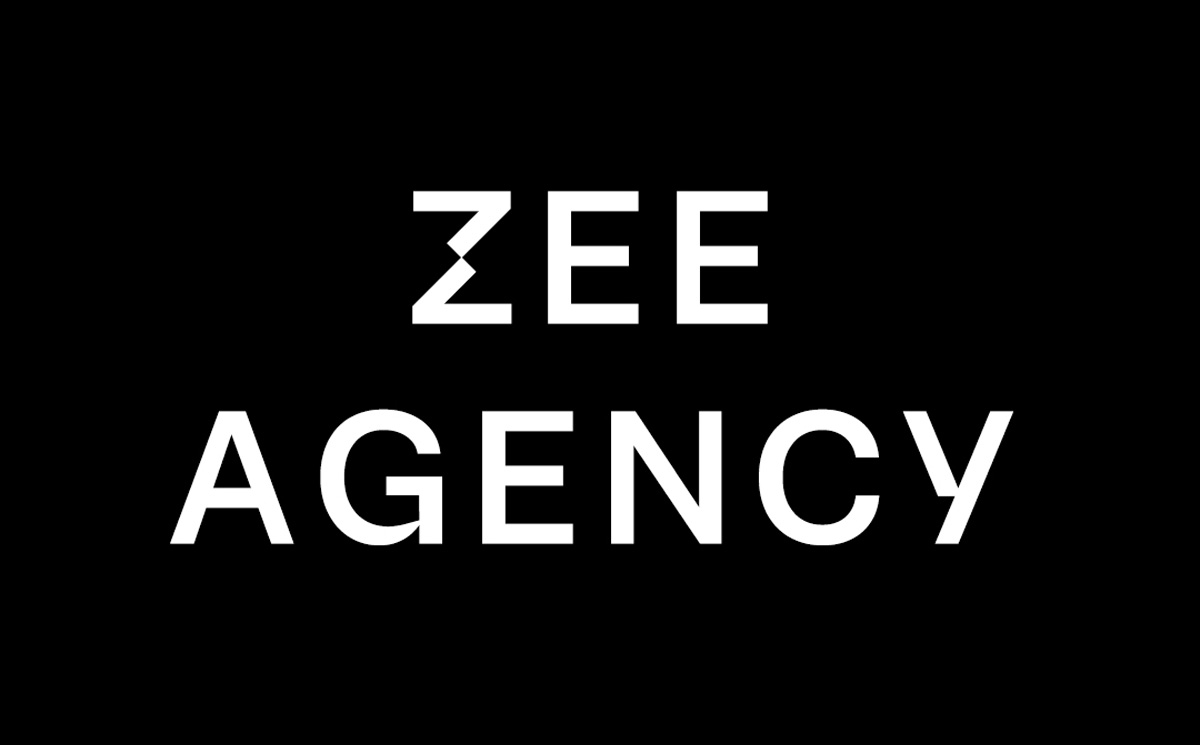
Font chữ chân phương là gì và phong cách tối giản trong đồ họa?
Font chữ chân phương là nhóm các phông chữ có cấu trúc ký tự rõ ràng, ngay ngắn và không quá cầu kỳ về mặt họa tiết. Từ “chân phương” trong ngôn ngữ Việt gợi nhắc đến sự mộc mạc, thành thật và chuẩn mực. Trong thiết kế, dòng phông này thường bao gồm các bộ Sans-serif hoặc Serif hiện đại với độ cao chữ đồng đều, giúp người đọc dễ dàng tiếp nhận thông tin mà không bị xao nhãng bởi các đường nét uốn lượn phức tạp.
Sức hút của phông chữ chân phương nằm ở tính minh bạch và sự vững chãi. Khi đơn vị ứng dụng kiểu chữ này vào hệ thống nhận diện, nó truyền tải thông điệp về một phong thái làm việc bài bản, đáng tin cậy.
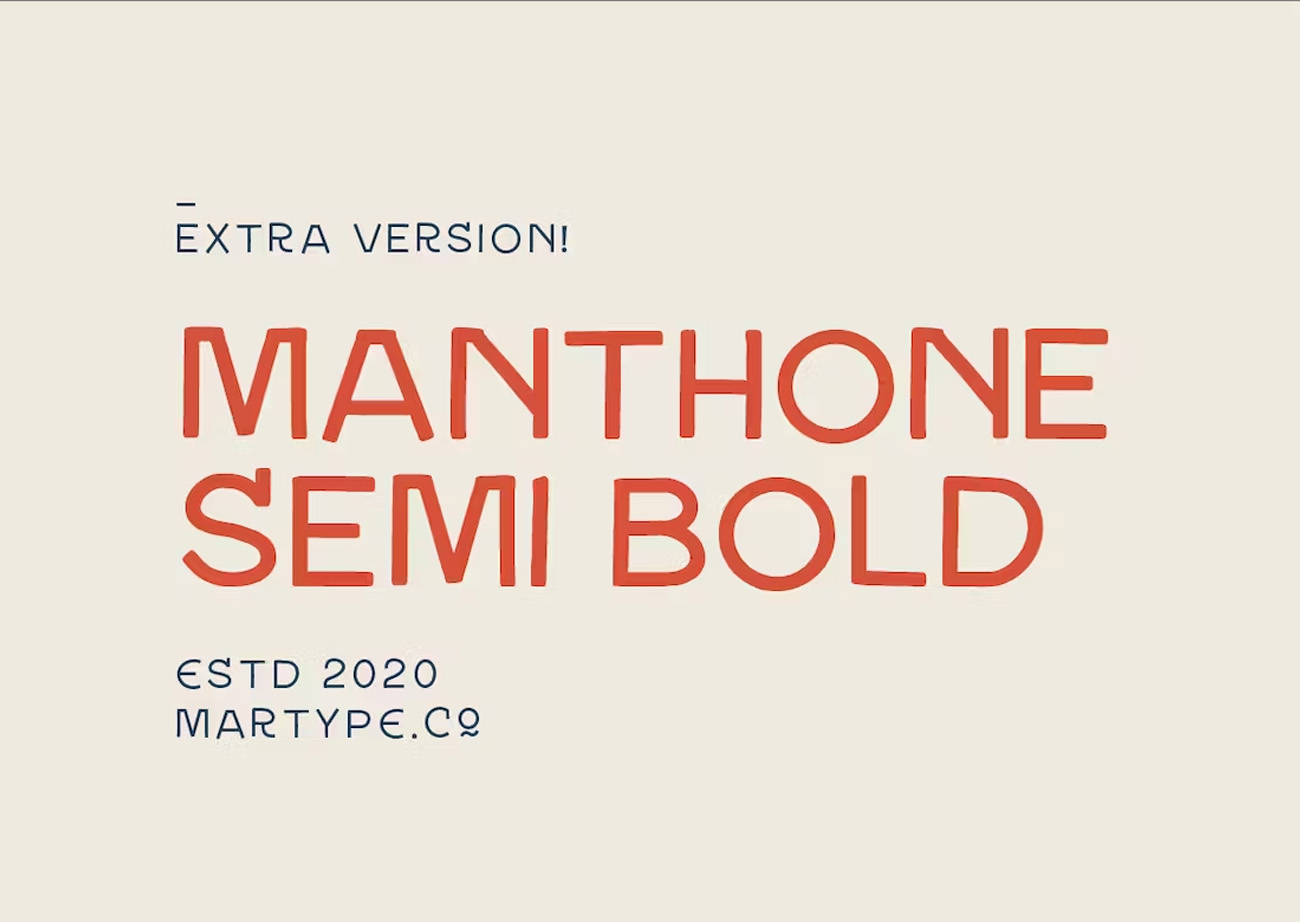
Việc sở hữu bộ font chữ chân phương chất lượng hỗ trợ đơn vị bảo toàn tính thẩm mỹ của các bản hồ sơ năng lực hay tem nhãn dán sản phẩm.
05 Ứng dụng phổ biến của phông chữ chân phương trong sản xuất in ấn
Vẻ đẹp trang trọng và tính đa dụng của mẫu chữ ngay ngắn này nâng tầm giá trị cho nhiều ấn phẩm truyền thông của đơn vị:
- Thiết kế hồ sơ năng lực và báo cáo thường niên: Font chữ chân phương giúp các trang giới thiệu thế mạnh doanh nghiệp trở nên chuyên nghiệp hơn. Khả năng hiển thị rõ nét ở các đoạn văn bản chi tiết giúp đối tác dễ dàng nắm bắt thông tin và tin tưởng vào năng lực của đơn vị bạn.
- Sản xuất bao bì dược phẩm và mỹ phẩm cao cấp: Sử dụng phông chữ này để in trên các dòng vỏ hộp giấy Ivory hay hộp cứng. Những nét chữ rõ ràng tạo cảm giác về sản phẩm có nguồn gốc tin cậy, dễ dàng tạo ấn tượng với phân khúc khách hàng coi trọng chất lượng.
- Gia công in UV trên các sản phẩm văn phòng: Logo và tên đơn vị dùng font chân phương được in trên bình giữ nhiệt kim loại hoặc sổ tay da. Độ sắc sảo của tệp vector giúp nét chữ hiển thị rõ ràng trên các bề mặt sẫm màu, tạo vẻ ngoài hiện đại và bền bỉ.
- Trang trí bộ ấm chén sứ tri ân đối tác: Hình ảnh chữ nghệ thuật dùng phông chân phương in nung trên men sứ trắng mang lại vẻ đẹp nhã nhặn, cổ kính, là hiện vật vinh danh tinh tế cho các buổi lễ ký kết hợp tác quan trọng.
- Khắc laser tinh xảo trên bề mặt gỗ và kim loại: Chữ chân phương khi khắc trên bìa sổ tay gỗ hoặc các khối pha lê kỷ niệm chương tạo độ sâu ấn tượng. Tệp chuẩn giúp máy khắc đi nét mượt mà, không bị cháy hay đứt đoạn các nét thanh mảnh.
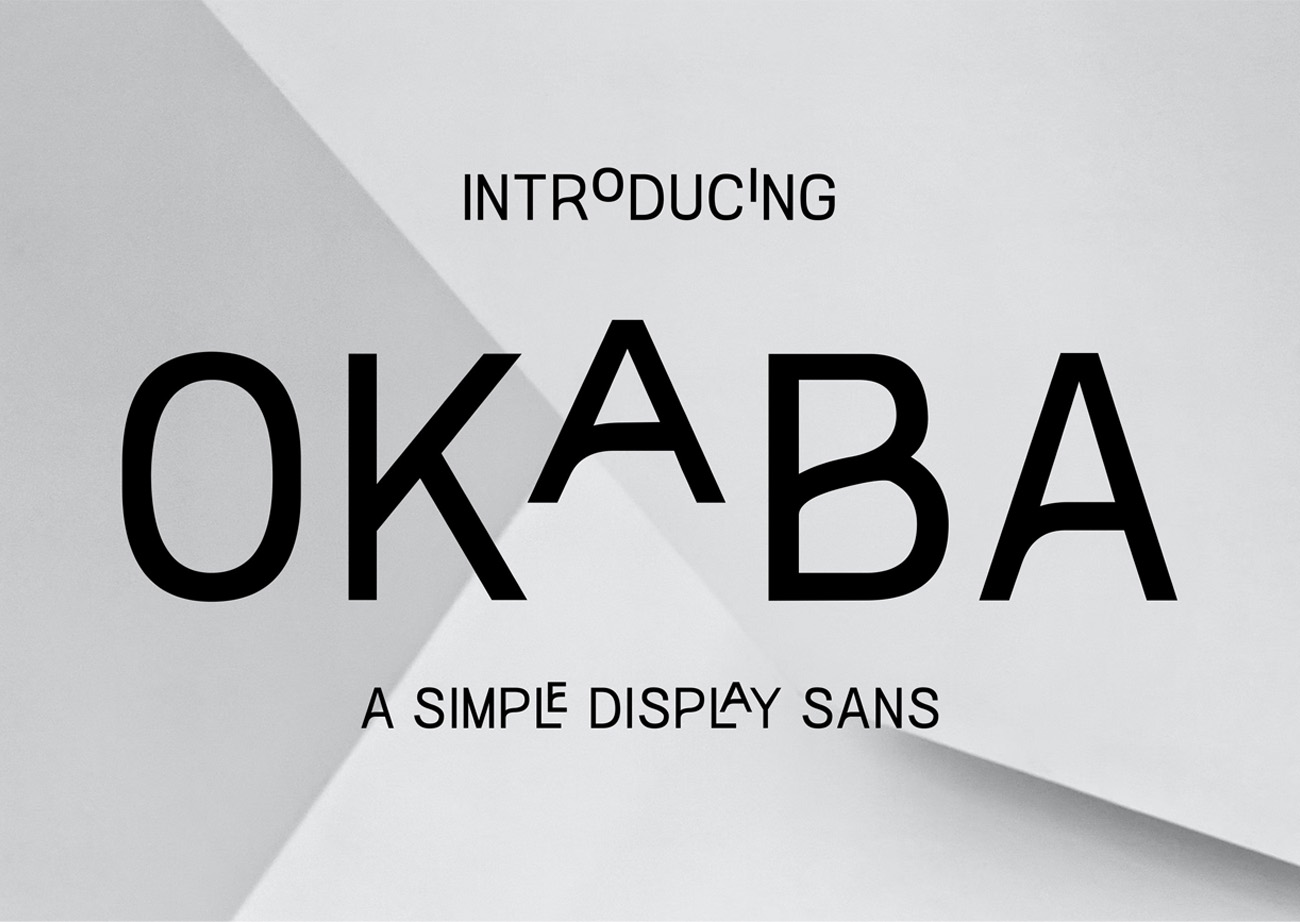
04 Tiêu chuẩn kỹ thuật khi xử lý font chân phương phục vụ in ấn
Để hệ thống ký tự hiển thị sống động và bền màu trên các thành phẩm thực tế như túi giấy hay hiện vật tri ân đối tác, nhà thiết kế cần lưu tâm:
- Kiểm soát khoảng cách dòng: Với các bản in sử dụng font chữ chân phương, việc thiết lập khoảng cách dòng thoáng đạt giúp văn bản dễ đọc hơn, nâng cao trải nghiệm cho người xem khi theo dõi các nội dung báo cáo dài.
- Tối ưu đường Path cho gia công bế nổi: Khâu này quan trọng khi sản xuất nắp hộp cứng dập nổi logo. Kỹ thuật viên cần làm mượt các điểm neo uốn lượn trong file thiết kế giúp khuôn kẽm thực hiện chính xác các đường viền chữ, tránh tình trạng rách giấy Ivory tinh tế.
- Thiết lập hệ màu CMYK chuẩn thương hiệu: Phông chữ này thường đi cùng các màu đơn sắc tối giản như đen đặc hoặc xanh navy. Bạn nên hiệu chỉnh hệ màu chuẩn và yêu cầu xưởng in mẫu thử để đảm bảo màu chữ sau in không bị ám xám hay mất sắc độ thiết kế.
- Điều chỉnh độ dày nét theo vật liệu: Khi in trên túi giấy Kraft có độ thấm mực cao, bạn nên chọn biến thể có nét dày vừa phải để chữ không bị mờ nhạt. Ngược lại, in trên giấy Ivory láng mịn có thể sử dụng các nét thanh để tạo vẻ thanh thoát.